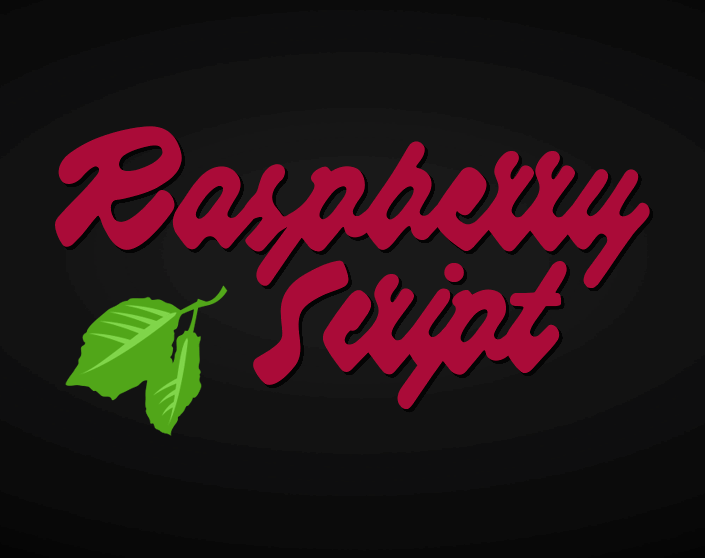
Raspberry Script Font
A Raspberry Script Font é uma deliciosa curva do coração para designers apaixonados por letras feitas à mão. Originada pelo designer Måns Grebäck, essa fonte adora explorar camadas sutis e nuances do escrita sem ser exagerada ou formal demais. Se você busca um estilo elegante e versátil que se mistura perfeitamente com a sua arte digitada à mão, esta é a escolha certa para seus projetos de design. Para adquirir uma licença comercial, visite o site da Måns Grebäck, www.mn.sg/raspberry-script. Caso tenha mais perguntas sobre este singular recurso gráfico, o FAQ do website também oferece um suporte atencioso: www.mn.sg/faq. Além disso, para aprender mais sobre seu talento e suas outras criações, visite a página pessoal de Måns Grebäck em www.mansgreback.com. É sempre uma boa ideia se juntar à comunidade do designer pelo Facebook, onde os fãs da fonte podem compartilhar ideias e experiências sobre como utilizam o Raspberry Script Font: http://www.facebook.com/mansgreback.